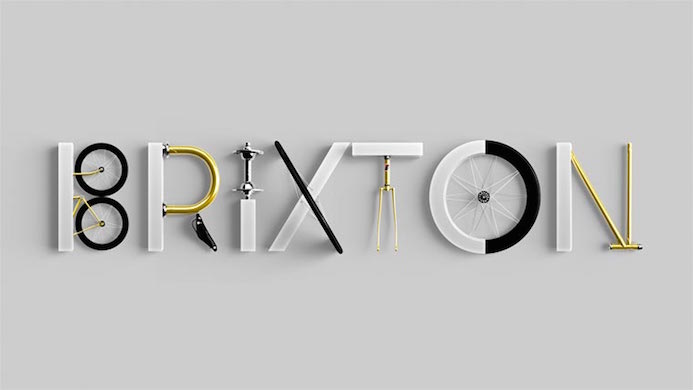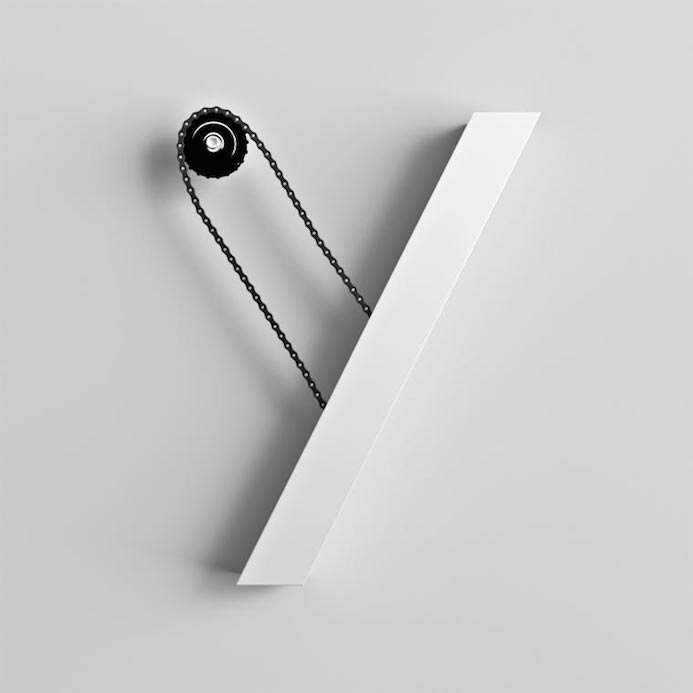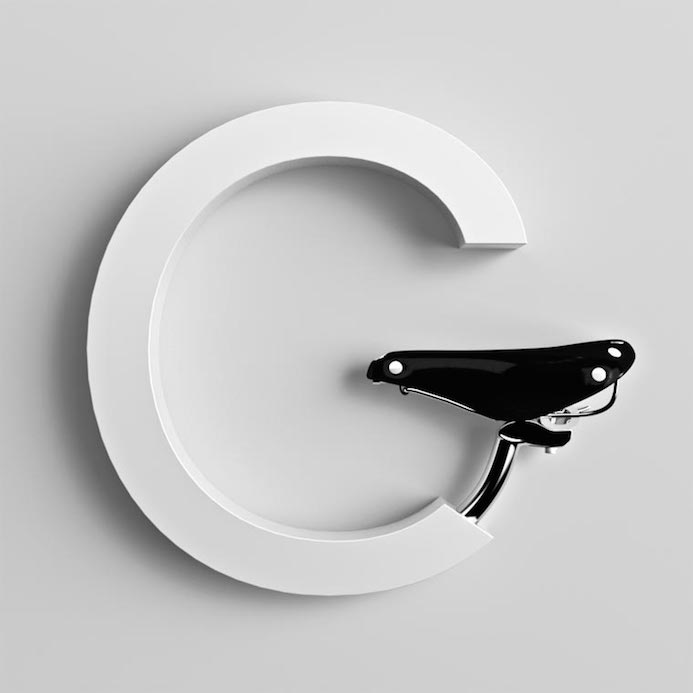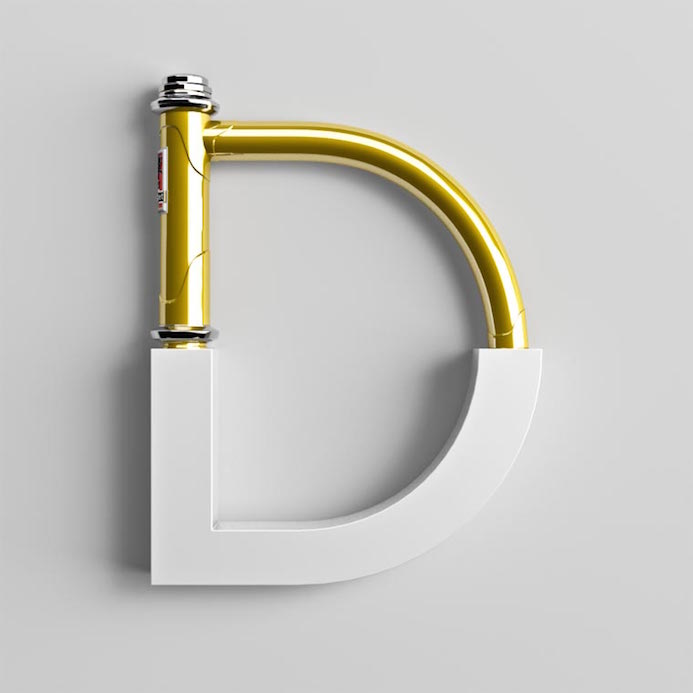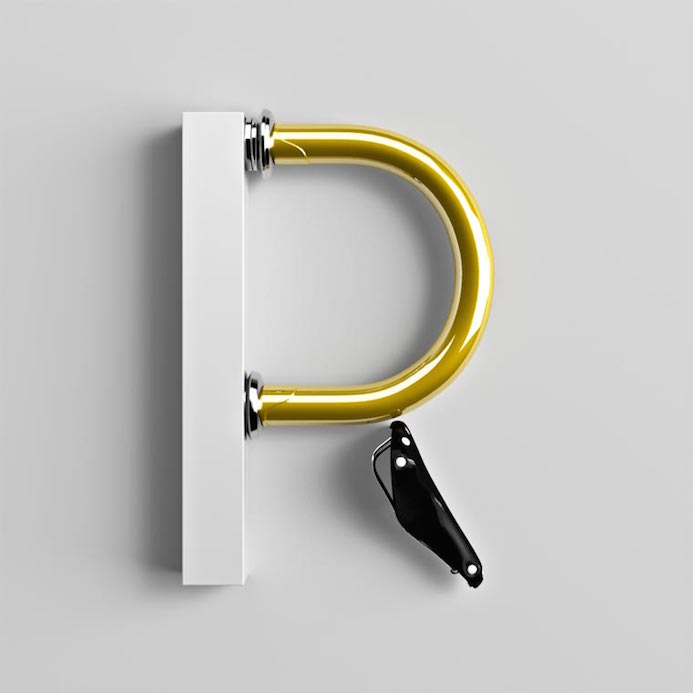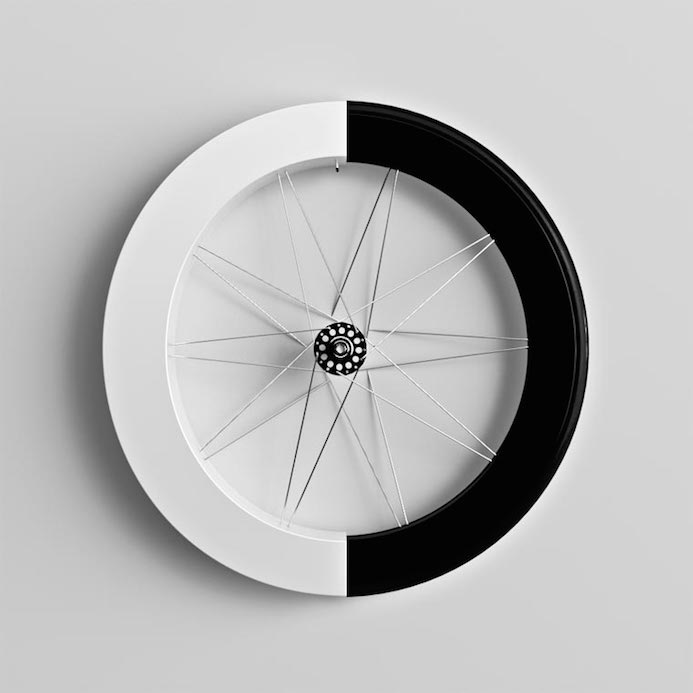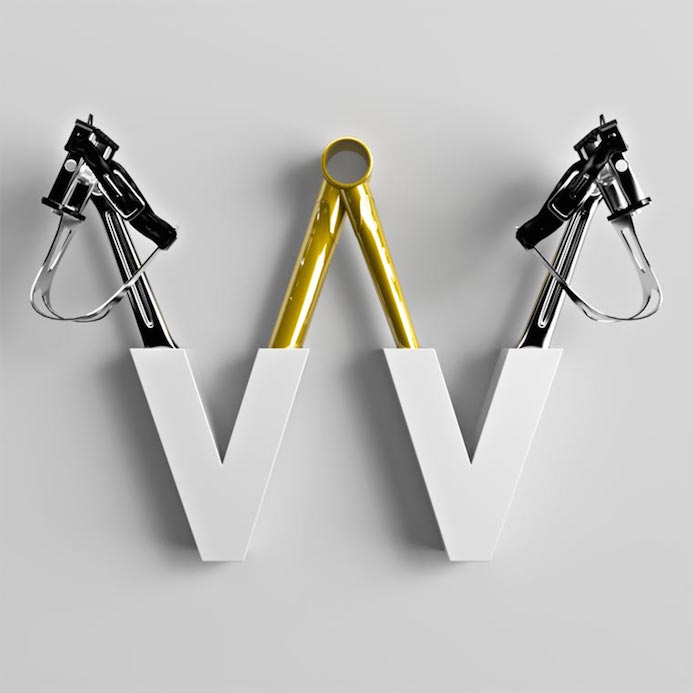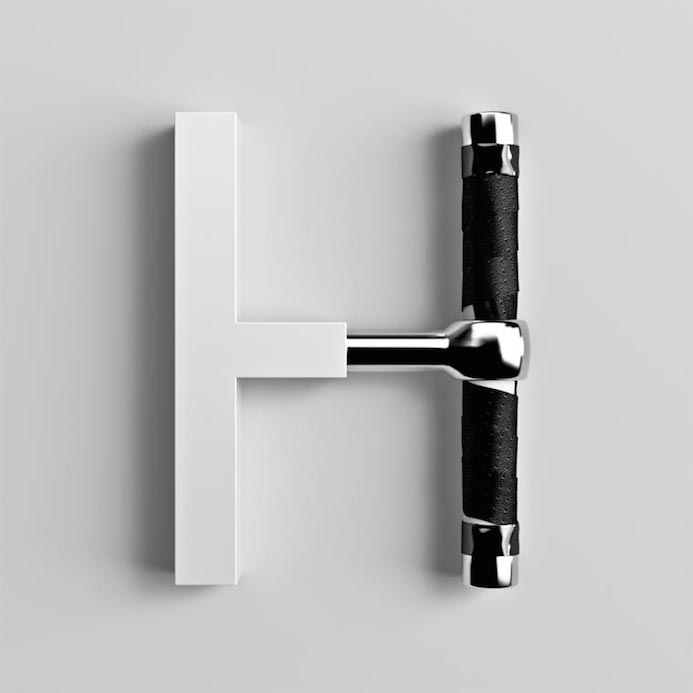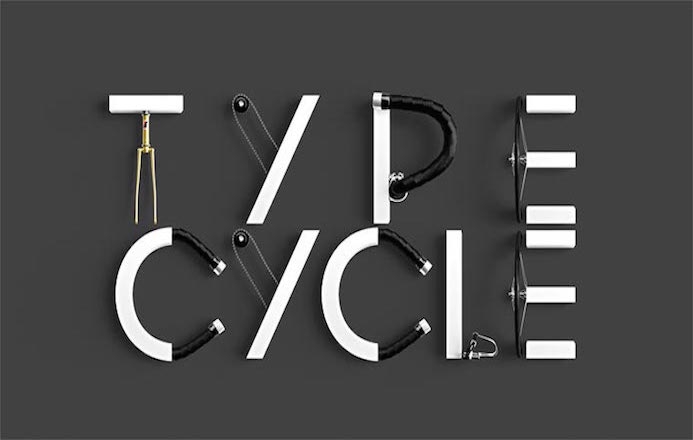
Depuis le temps que nous voulions réaliser une sélection de typographie spéciale "bicycle", nous avons enfin trouvé notre bonheur ...
Et c'est Marcel Pierarski qui nous l'offre avec cette série de typographie qui utilise des éléments d'un vélo pour former une lettre !
Un travail smart que nous vous invitons à découvrir :